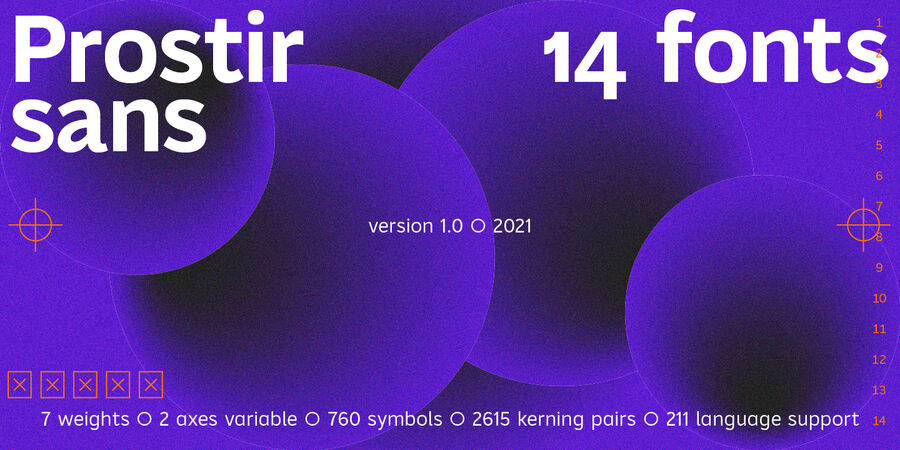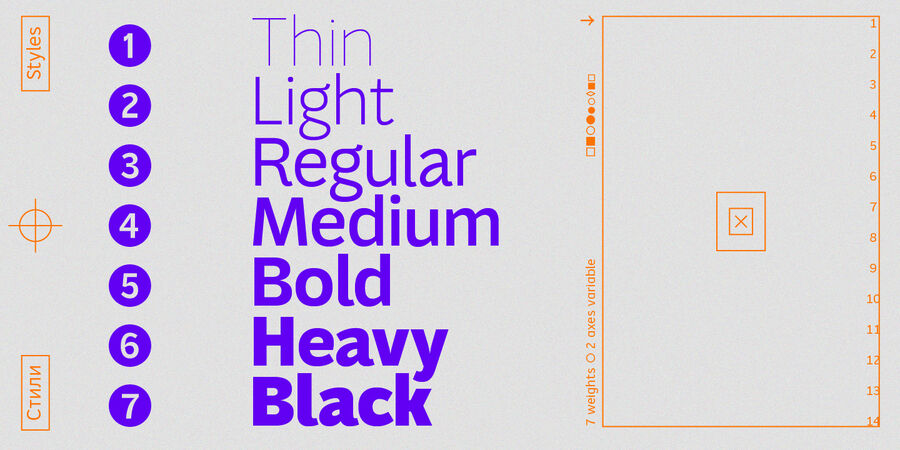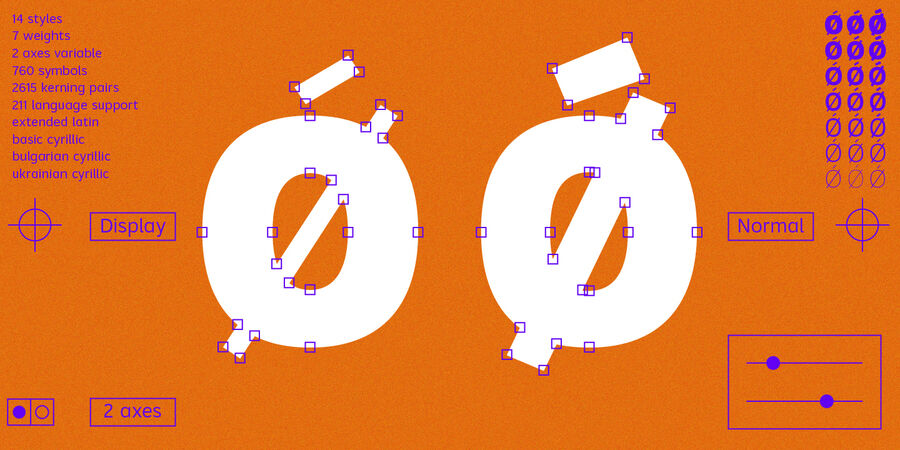
Prostir Sans – потужний гуманістичний гротеск. Він прагне бути «робочою конячкою», яка виконує практично будь-яку роботу без зайвих проблем, залишаючись досить виразним шрифтом. Має велику висоту рядкових літер і маленькі пастки для фарби. Шрифт виглядає емоційно та вільно, поєднуючи плавні вигини та контрастні з'єднання. Він складається з 2-х умовних частин – Основної та Акцидентної, які відрізняються товщиною діакритичних знаків та додаткових елементів. Цей контраст додає незвичайної ритмічності та жвавості. Гарнітура має 7 градацій за насиченістю та підтримує варіативність, що регулюється по двох осях. Це дозволяє точно налаштувати потрібний стиль. Загальний набір гліфів: 753 гліфи; 14 накреслень (7 ваг + альтернативні накреслення); Підтримка понад 210 мов (розширена латинка, базова кирилиця + болгарська кирилиця). Можливості OpenType: Пропорційні, мінускульні, табличні цифри, цифри у колах, дроби, індекси; Стрілки, Стилістичні набори, Лігатури, Регістрозалежні форми. Накреслення Prostir Sans Display Heavy є безкоштовним для безлімітного використання на умовах ліцензій «Десктоп» і «Веб». Шрифт розробив Максим Кобузан у 2021 році.
15 накреслень
Асоціації з сімейством шрифтів Prostir SansОсобистість і характер гарнітури:
Простий, гладенький, універсальний, врівноважений, комфортний, приємний, зручний, якісний, рівний, монотонний, зрозумілий, нейтральний, спокійний, доступний, чистий, космополітичний, ненав'язливий, помірний, технічний, сучасний, глобалізований, глобалістічний, лаконічний, практичний, довірчий, міський, легкий, свіжий, затишний, ритмічний, мінімалістичний, делікатний, прохолодний, модний, худий, тонкий, невагомий, прозорий, інтимний, крихкий, повітряний, дротяний, непомітний, діловий, серйозний, впевнений, сильний, переконливий, формальний, авторитетний, важливий, міцний, значний, твердий, солідний, гучний, яскравий, виразний, характерний, помітний, мотивуючий, крутий, амбітний, потужний, важкий, масивний
Місто, суспільство, гігієна, чистота, дієта, краса, косметика, коворкінг, банкнота, йога, вода, здоров'я, парфумерія, лосьйон, туалетна вода, дизайн, шампунь, бізнес, навігація, транспорт, аеропорт, метро, ліки, логістика, автобус, торгівля, монета, паливо, енергетика, урбаністика, тренажери, інструмент, кіно, гра, вантажівка, розваги, відпочинок, бар, нічний клуб, тусовка Гарнітура має ознаки стилів:
— Гарнітура асоціюється з віком: